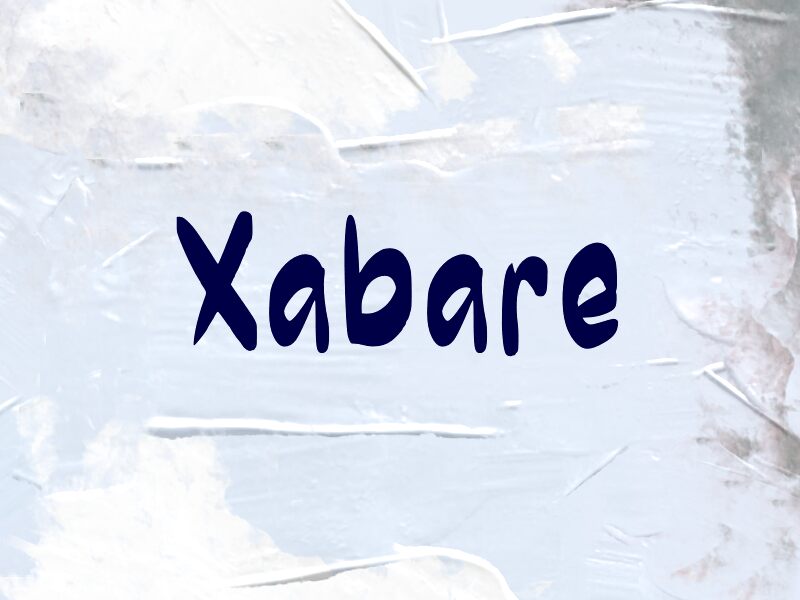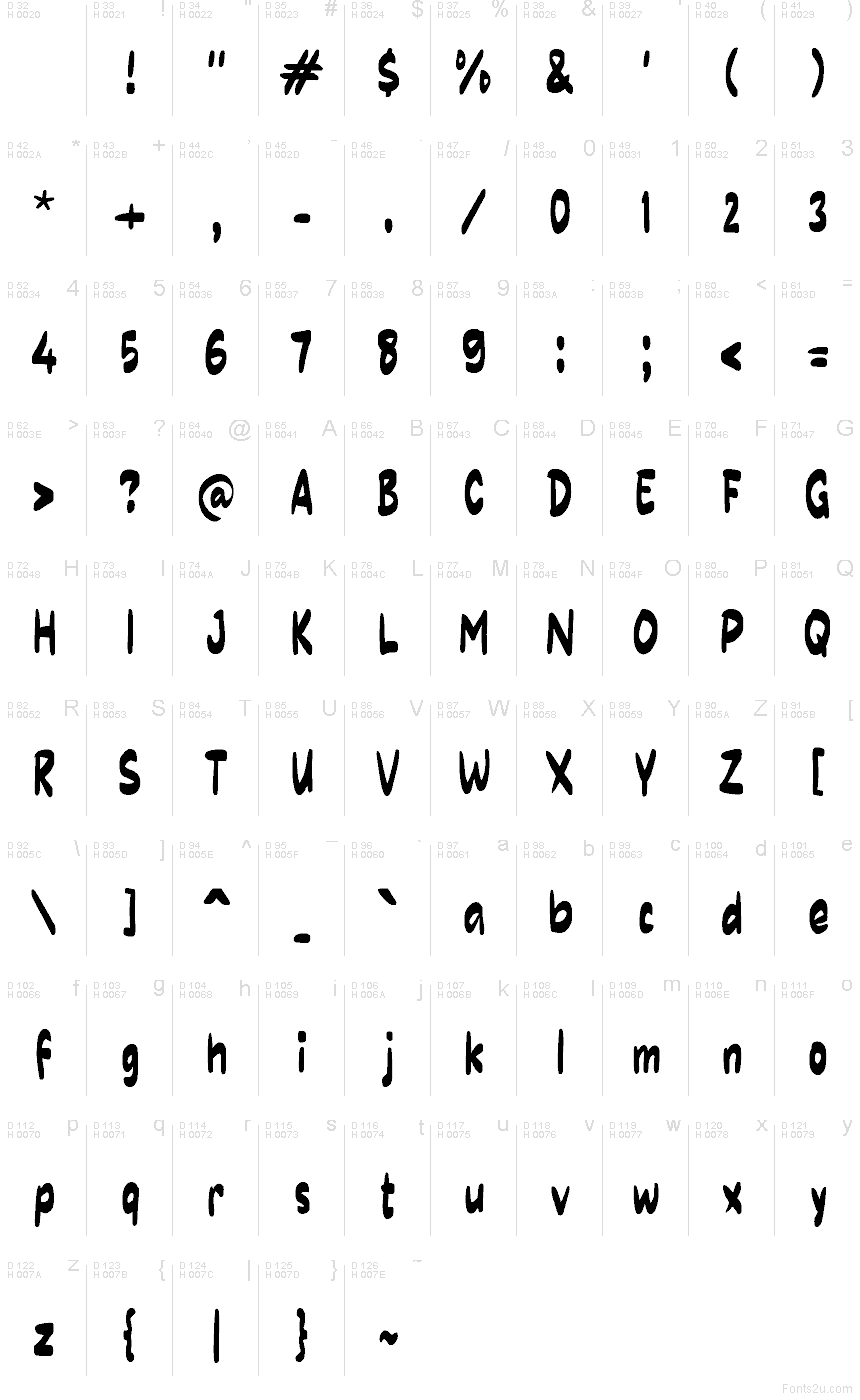
Xabare, créée par Wep, est une police pinceau gratuite au rythme rapide et spontané. Ses lettres se distinguent par des traits épais et arrondis aux extrémités effilées, conférant aux formes un dynamisme décontracté qui rappelle davantage le marqueur ou la brosse de signalétique qu’une écriture formelle. Sortie en 2025, elle dégage une énergie fraîche et authentique.
Elle est idéale pour les titres d'affiches, l'identité visuelle de cafés, le packaging, les visuels de réseaux sociaux et les titres de couvertures où une police gratuite doit rester informelle sans tomber dans le mignon. Grâce à sa texture de pinceau large et simple, Xabare brille particulièrement dans les mises en page d'affichage court, les cartons de titre et les logos, là où son mouvement peint et vif peut vraiment s'exprimer.
Xabare
Présentation et spécimen de la police Xabare
Table des caractères de la police Xabare
Table des caractères de Xabare : Latin de base, page 1
Glyphes de la police Xabare — Latin de base, page 1